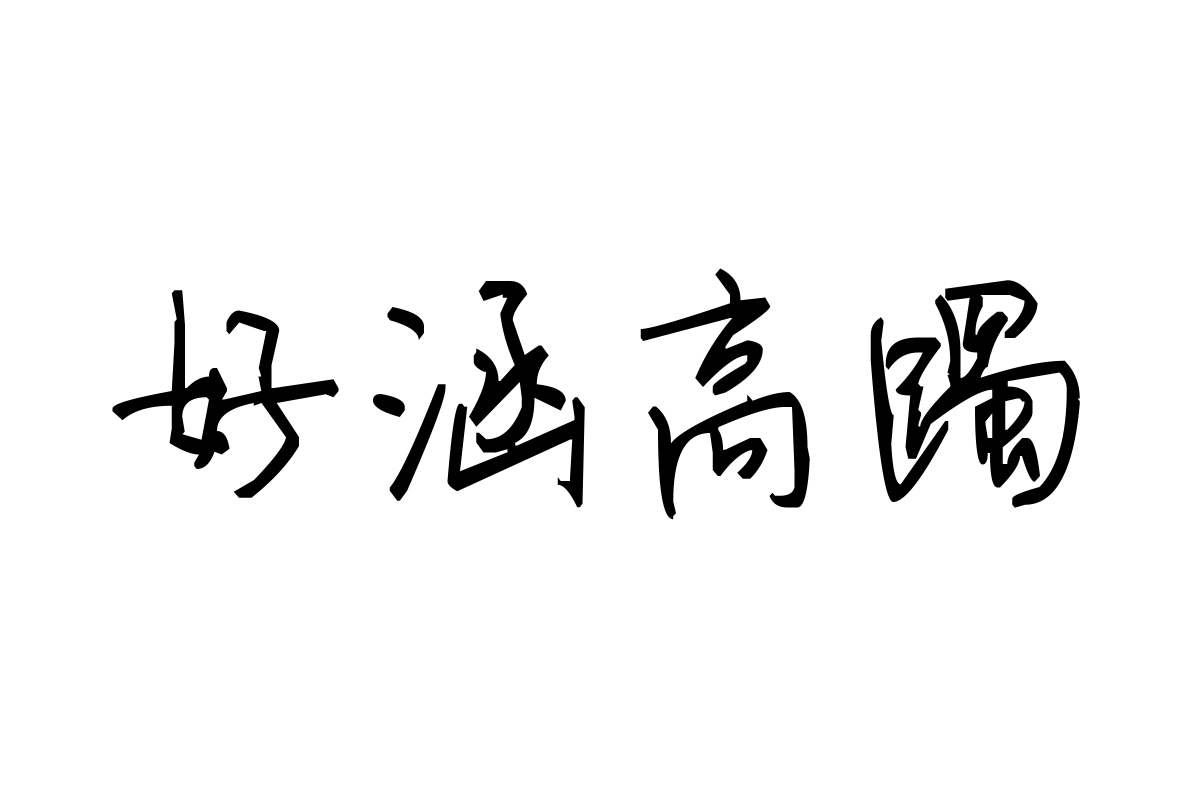
米开风情月意体是一种具有独特风格的字体,它融合了现代和传统的元素。这种字体的特点是:
1. 线条流畅:米开风情月意体的线条流畅自然,给人一种优雅的感觉。
2. 结构紧凑:这种字体的结构紧凑,使得文字看起来更加整洁有序。
3. 风格独特:米开风情月意体的设计风格独特,既有现代感,又不失传统韵味。
4. 适用广泛:这种字体适用于各种场合,如广告、海报、书籍等。
5. 易于识别:由于其独特的设计风格,米开风情月意体很容易被人们所识别和记住。
米开风情月意体